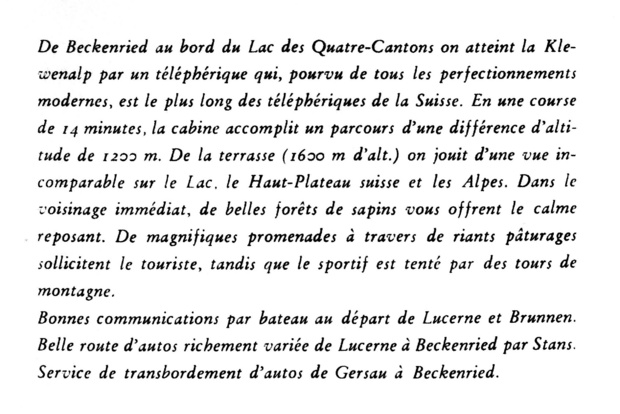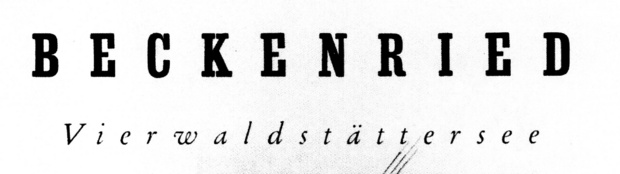
noch einmal: Stanserhorn
Bei der Suche nach zwei weiteren Schriften hätte ich gerne Eure Hilfe. Die eine ist nahe an der Garamond ITC mager kursiv, auch an der Caslon 224 kursiv, aber ich bin mir nicht ganz sicher und finde auch keine "käufliche" Version davon. Markant ist ja besonders das kleine "w". Die andere, in meinen Augen sehr schöne Egyptienne, finde ich auch nicht heraus.
Die hier sieht gan ähnlich aus.
Die Stempel Garamond könnte vom w her auch passen ...
... oder Berthold Garamond
In dem Beispiel wirkt mir aber der Anstrich vom n sehr eigenartig :-?
… Kannst Du mir auch etwas zur "Egyptienne" sagen?
Die käme sehr nahe: